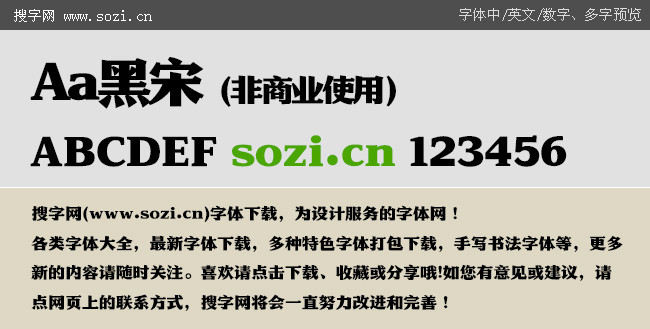
Aa黑宋
搜字網給大家提供一款Aa黑宋(非商業(yè)使用)中文字體下載,該字體是一款醒目的標題字體,表現(xiàn)出鋒銳又具有厚重的形態(tài)。具有強烈的視覺沖擊力,清新簡明。適合書裝設計、包裝設計、海報設計等應用(此字體為個人非商用版,商用可以聯(lián)系QQ:1006760504)。